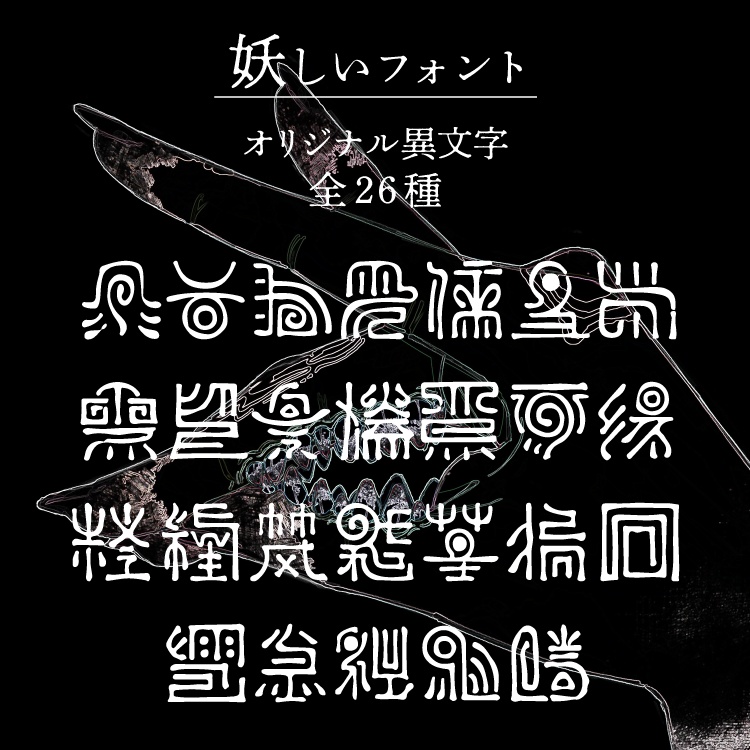
妖しいフォント
どこで生まれたのか、いつから存在しているのか、誰も知らない。 それが大昔の人間の手によるものなのか、それとも人ならざる「何か」によって生み出されたのかすら謎に包まれている。 いつしか人々はこの妖しい異文字を畏れと興味をもって扱うようになった。 とかなんとか色々妄想しながら作りました(ハズカシ!) じゃじゃ馬フォントですが上手に扱えるぜという方はぜひ。 ◉フォント形式:OpenTypeフォント ◉収録文字 収録文字数26字。アルファベットに紐づけられていますので全角・半角英数字でご使用いただけます。 ◉確認事項 ・商用・デザイン用途(印刷物・ゲーム・アプリ・映像・動画・ロゴ・同人作品)に使用でき文字の加工・変形も可能です。※著作権を放棄するわけではございません。 ・二次配布禁止 ・自作発言禁止 ・AI学習禁止 ・クレジットに関しては記載いただけたら嬉しいですが自由にしていただいて構いません。 以上になりますが他に気になることがあればお気軽にお尋ねください。